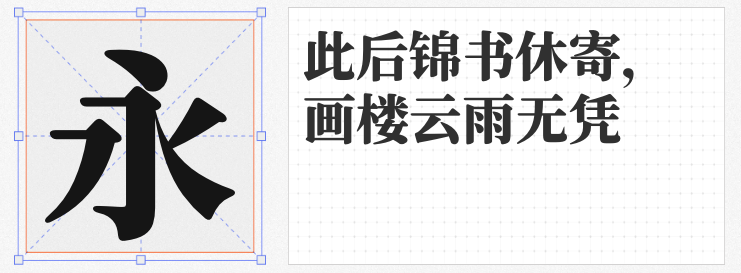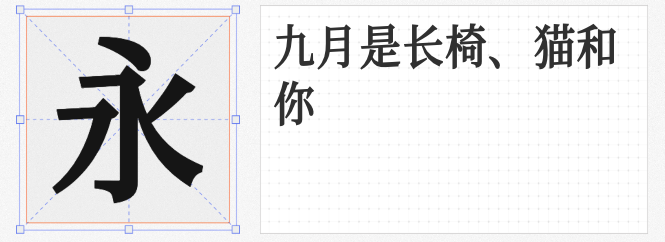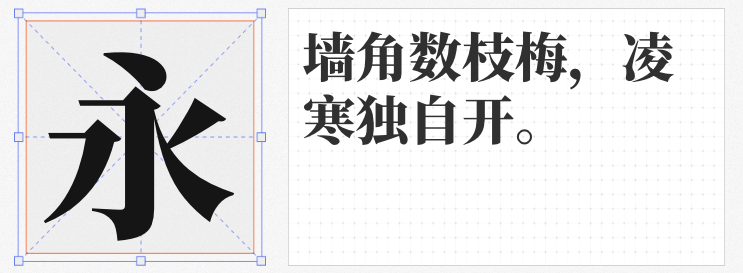
在平面设计中,宋体以其独特的文化韵味与现代感成为东方美学的经典载体。本文精选四款免费可商用的宋体字库,兼顾传统底蕴与创新设计,助力设计师打造兼具实用性与艺术性的作品。
作为Adobe与Google联合推出的开源字体,思源宋体覆盖简体中文、繁体中文、日语、朝鲜语四大东亚语言,并支持拉丁语、希腊语、西里尔文字。其7种字重(含Heavy)提供丰富的层次选择,65,540个字形确保多语言排版的一致性。CN Heavy版本以厚重笔画强化视觉冲击力,适合标题、海报等需要突出存在感的场景,同时保留宋体的典雅骨架,是国际化设计的理想选择。
基于新愚公和谐宋改造的猫啃网文明宋-S,通过微调字宽比例解决了原版长宽比失调的问题,整体视觉更协调。作为免费商用字体,它保留了宋体的传统结构,同时以简洁的笔画处理提升现代感,适用于正文排版、品牌标语等场景,尤其适合需要平衡传统与现代风格的项目。
香萃潮汐宋以突破性设计打破宋体常规:圆角处理与笔画粘连赋予字体柔和质感,横细竖粗的强烈对比增强视觉张力。其清新风格适配书刊、包装设计,而“藕断丝连”的笔画特征更暗藏恐怖题材的戏剧性潜力,为设计师提供跨风格的应用可能。
基于思源宋体优化的寒蝉锦书宋,通过圆角修饰与字重重构,打造出更易阅读的温润宋体。Heavy版本在保留传统宋体结构的同时,以均衡的粗细比例提升文字密度,适合长文本排版、书籍装帧等场景,传递“锦上添花”的美好寓意。